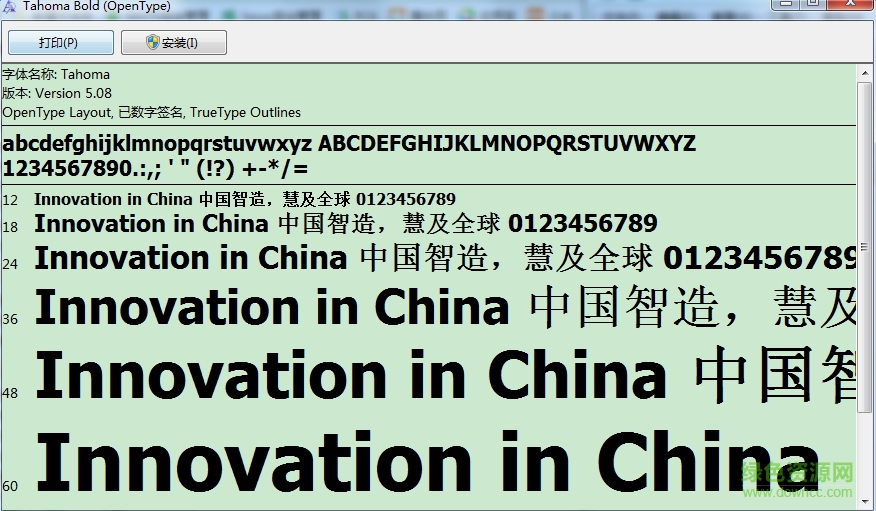
tahomabd.ttf是一款非常實(shí)用的英文字體。這款字體字形端正大方,結(jié)構(gòu)簡(jiǎn)約,可廣泛應(yīng)用于平面設(shè)計(jì)、廣告設(shè)計(jì)、報(bào)紙雜志、正文標(biāo)題等領(lǐng)域,整體效果非常出色,喜歡的朋友歡迎來(lái)綠色資源網(wǎng)下載!